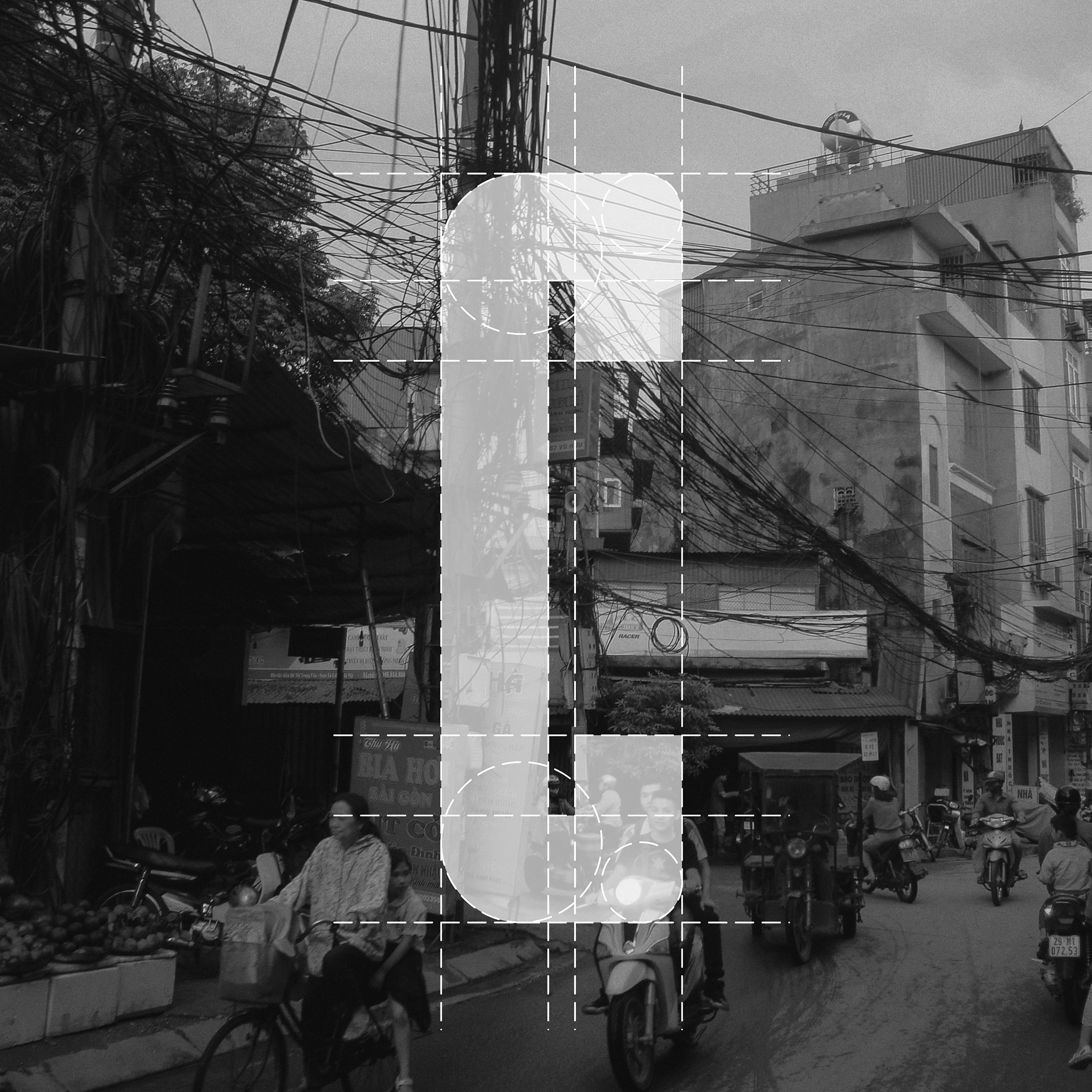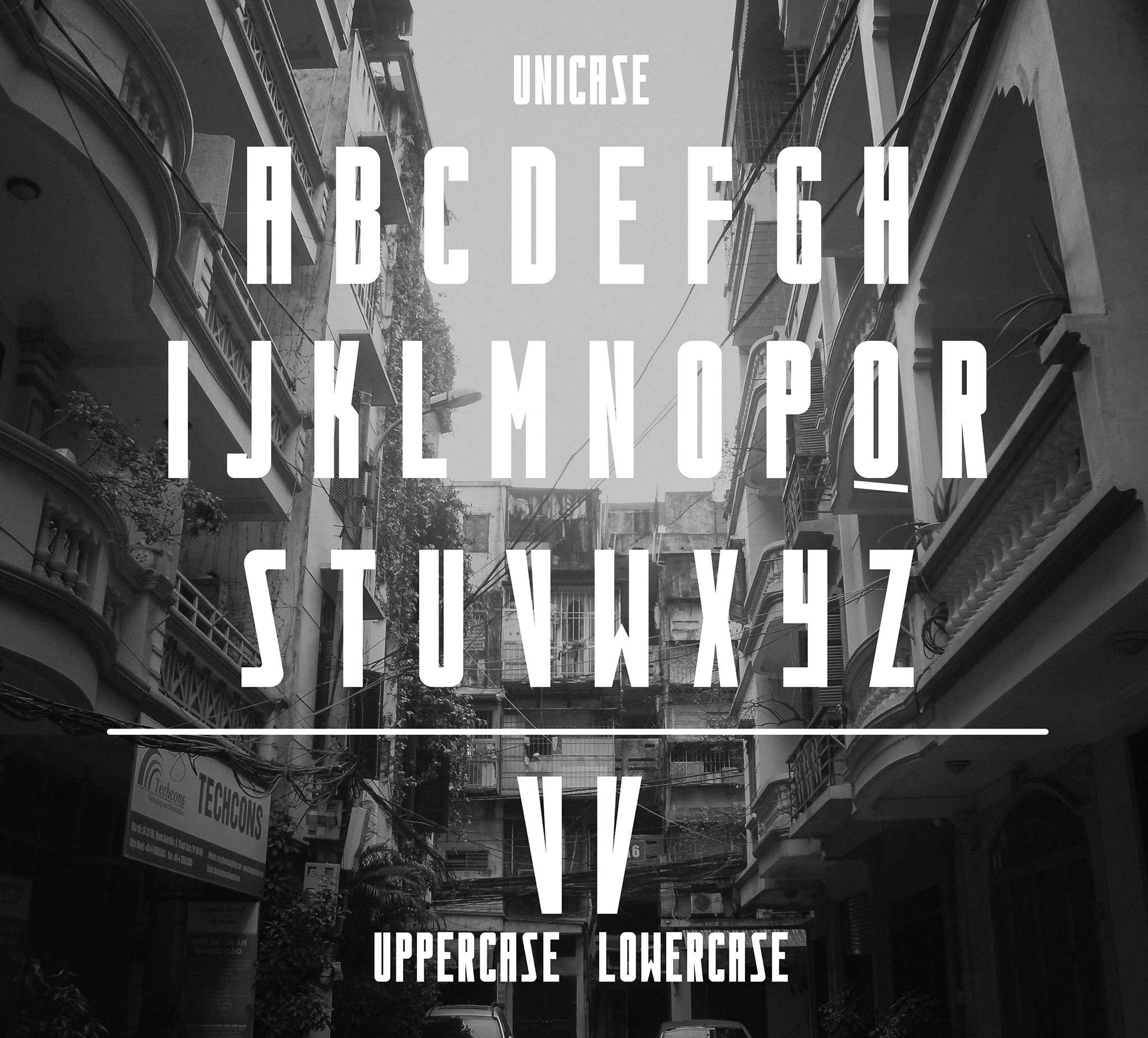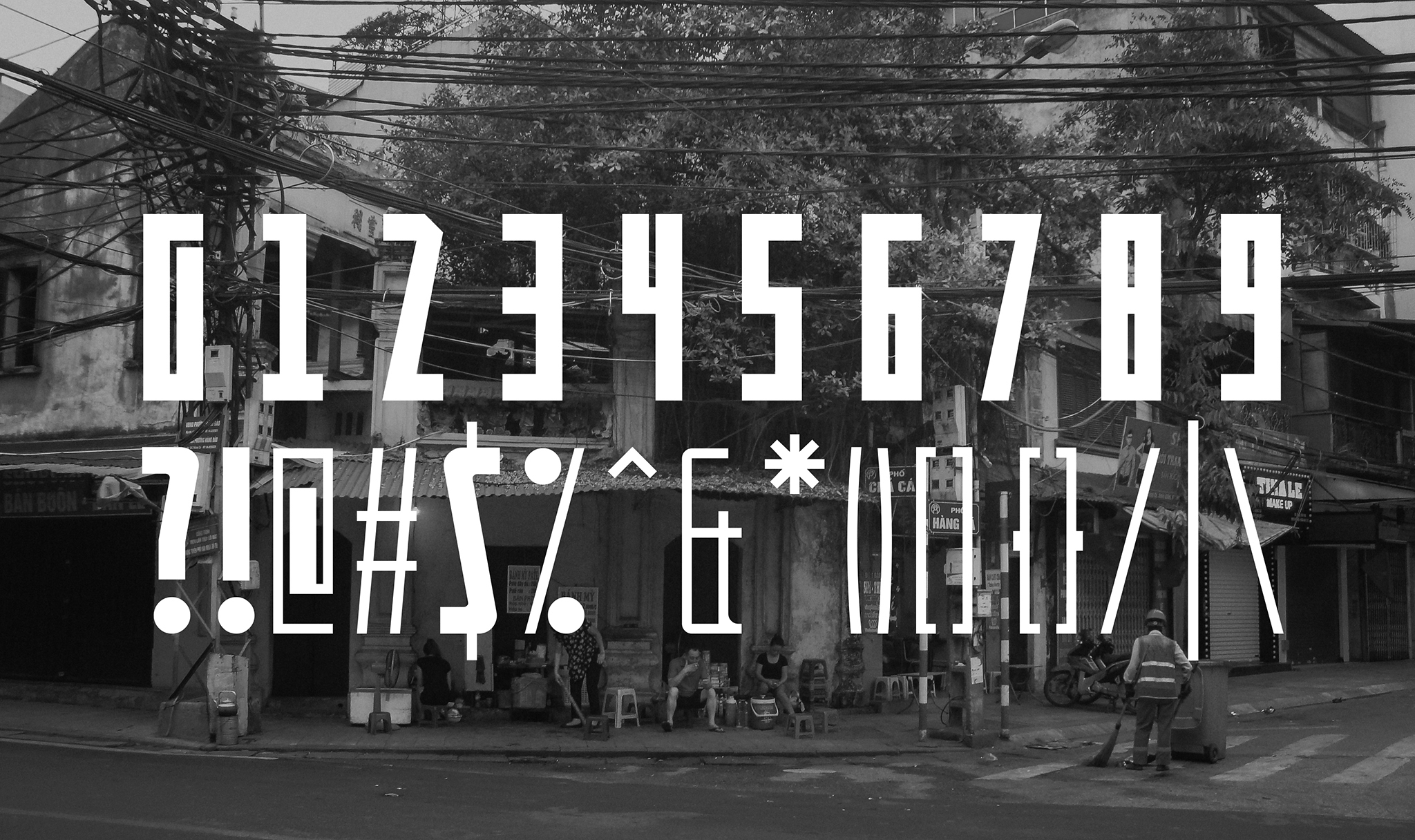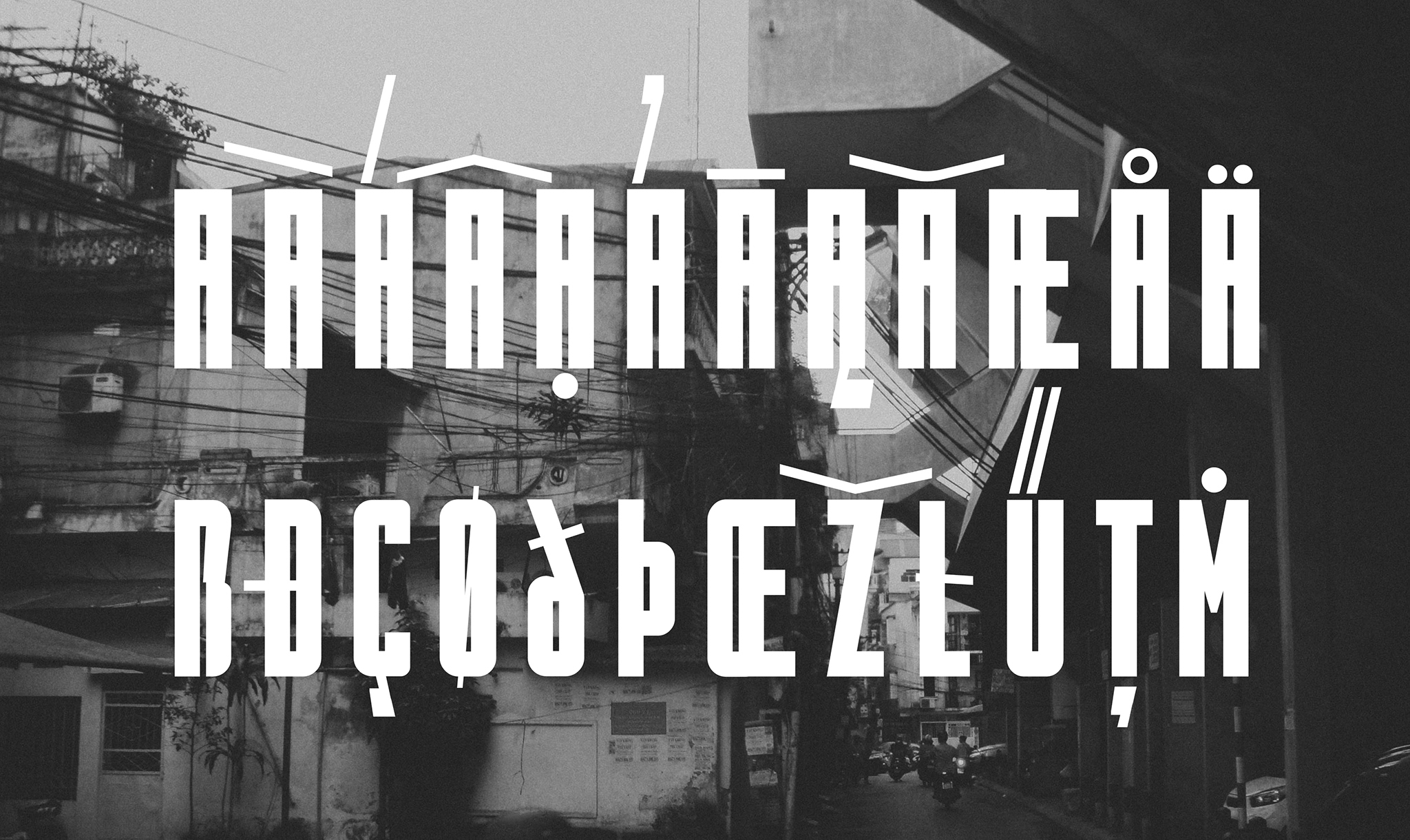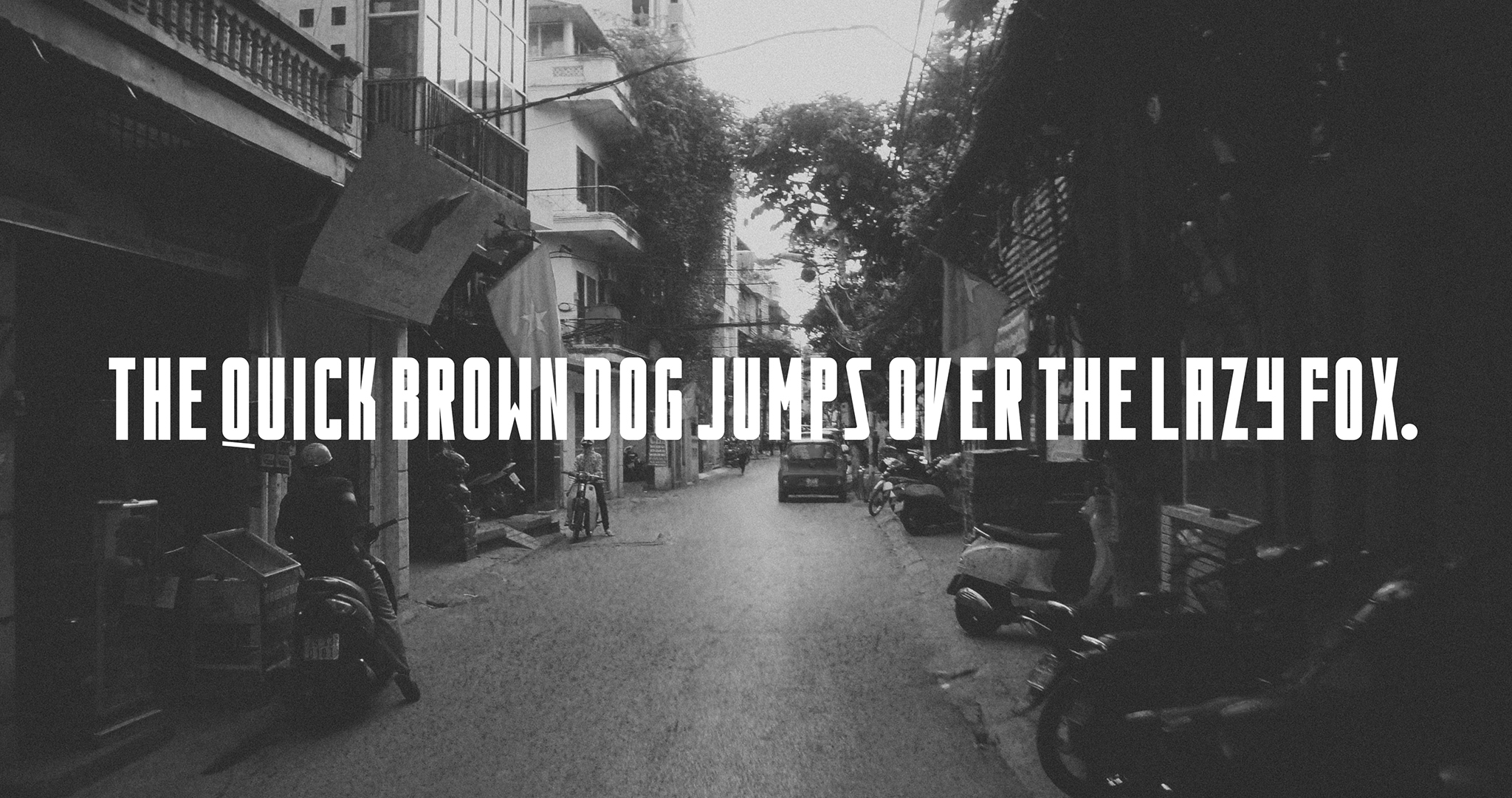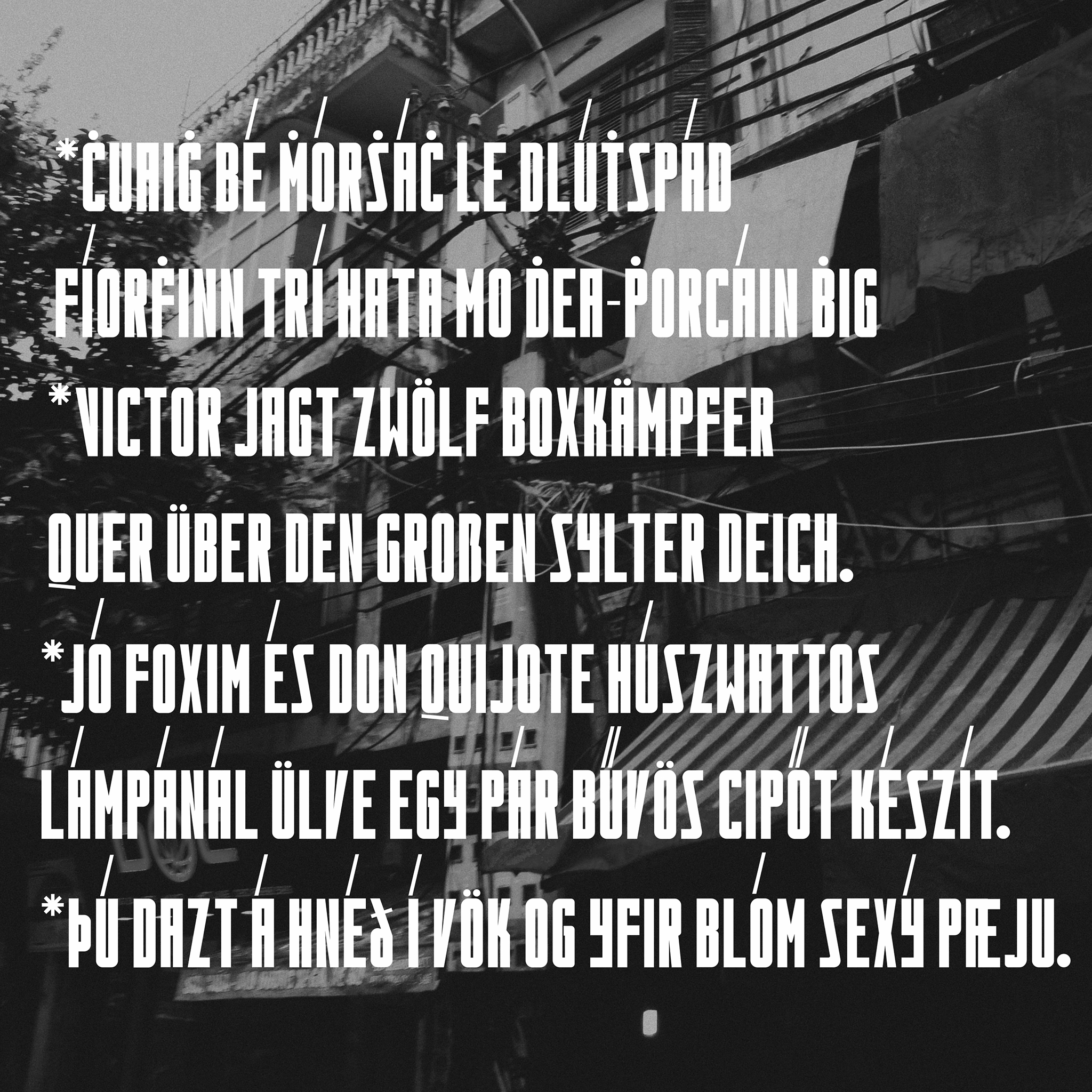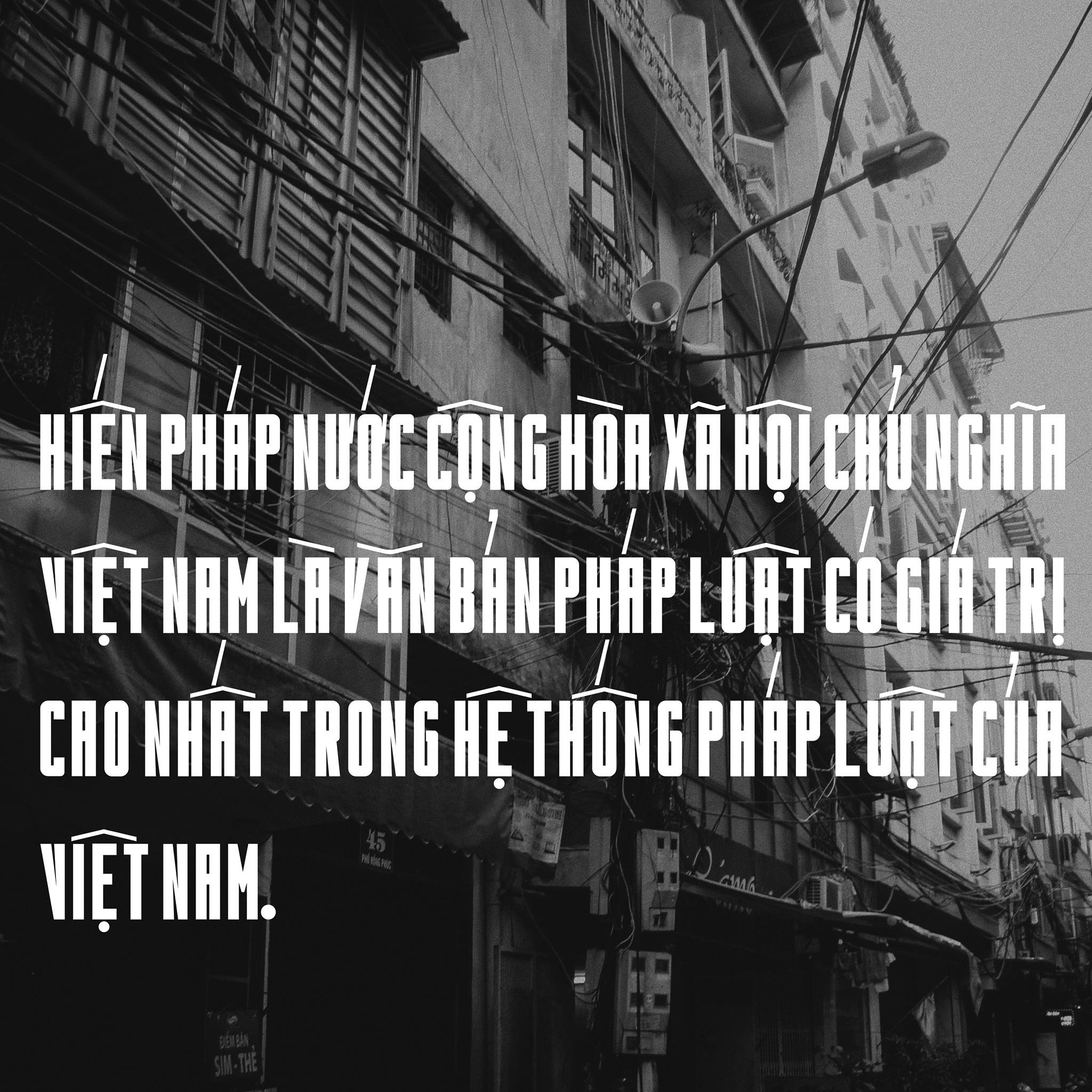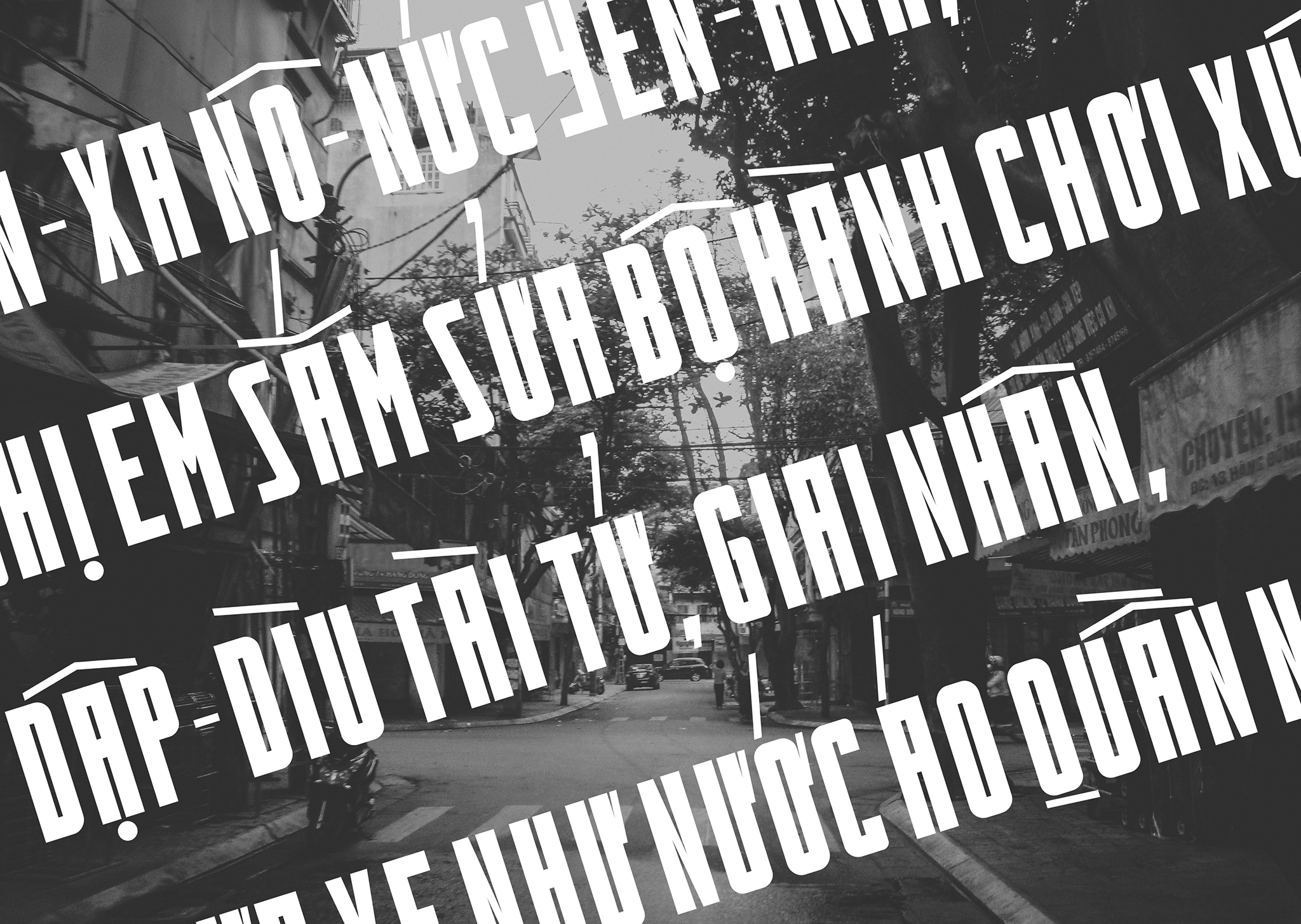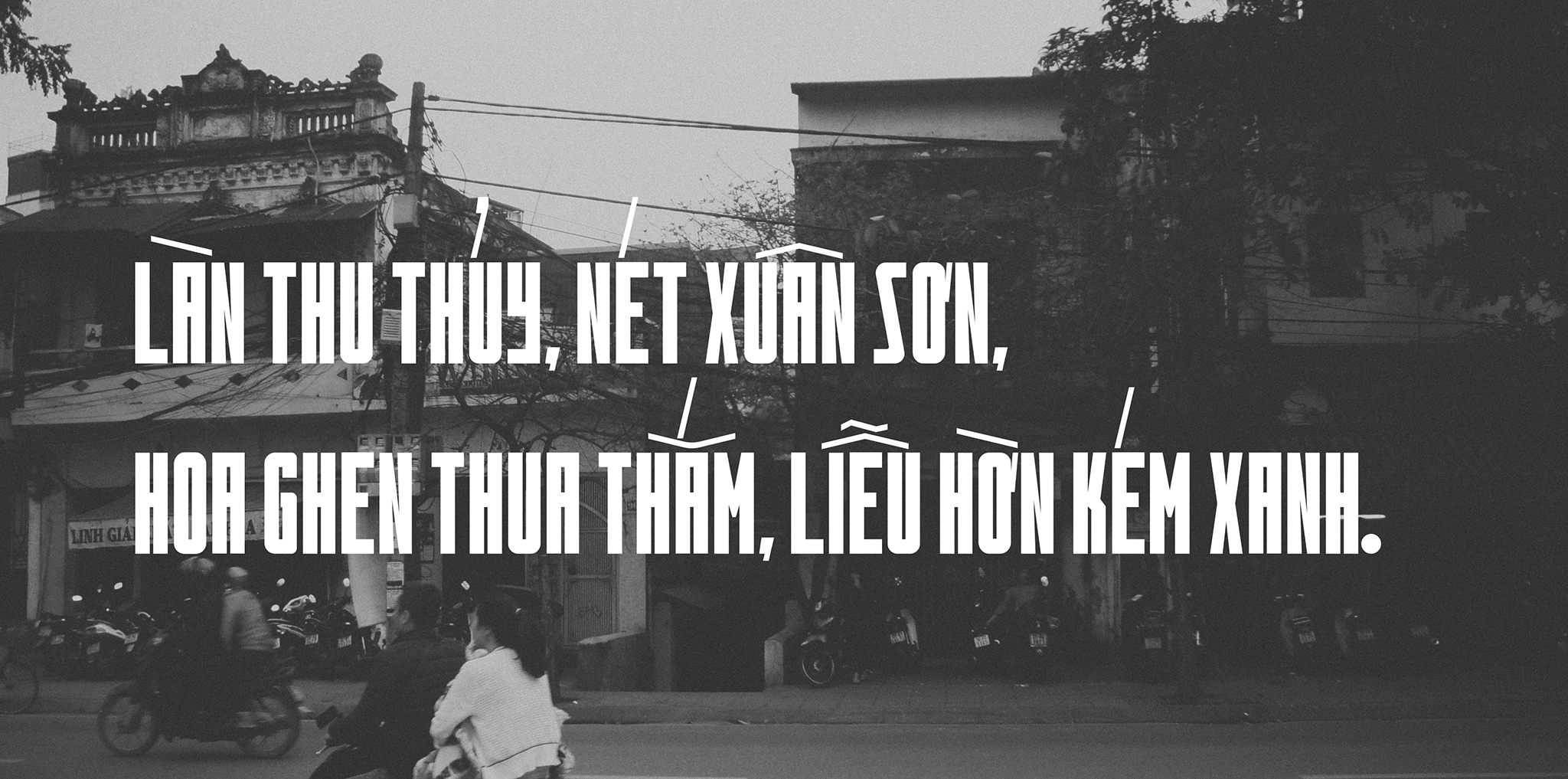
Cotdien typeface (tiếng Việt: Cột điện) là một mặt chữ được tạo ra bởi Mạnh Nguyễn, một kiểu chữ thiết kế tại Việt Nam và là người yêu những nét chữ vẽ tay cổ điển và biểu ngữ tuyên truyền tại Việt Nam từ thế kỷ trước và cố gắng mang ý nghĩa chúng vào một phần công việc của chính mình. Mặt khác, các kiểu chữ cũng bị ảnh hưởng bởi sự hiện diện của “cột điện” xuất hiện ở vô số các con đường xuyên suốt từ thành thị tới vùng quê Việt Nam.
Cotdien là một kiểu chữ miễn phí – sans serif dùng các hình học số; do đó, nó tạo ra một nét thẩm mỹ cho việc thiết kế tạp chí, logo thương hiệu, vv, .. với một vẻ đẹp rất cổ điển và hiện đại ấn tượng thẩm mỹ được tạo ra bằng kinh nghiệm của Mạnh về nhiếp ảnh đường phố.